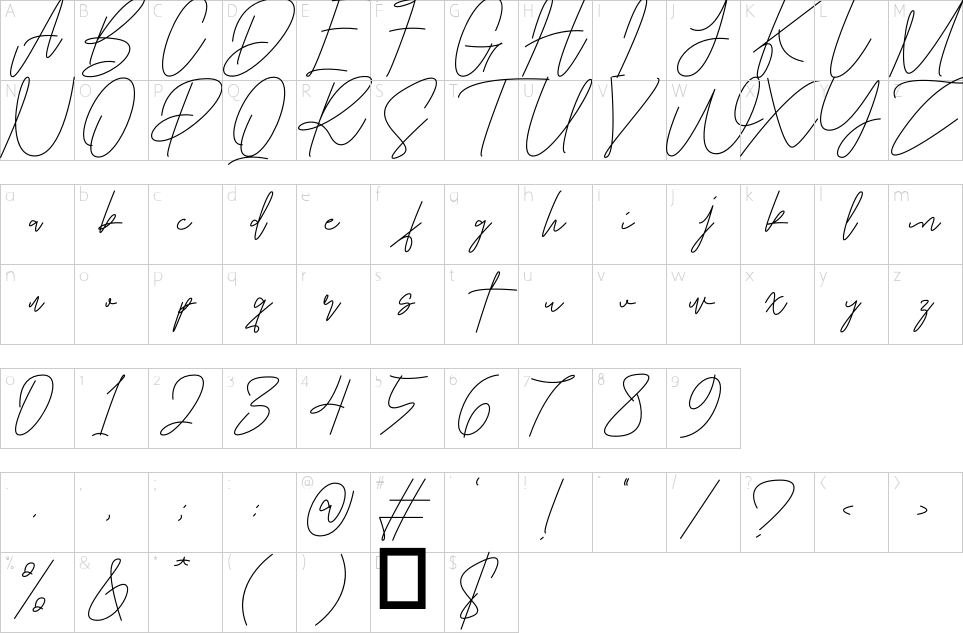
A fonte Samarotan é uma opção grata para designers, criadores de blogs e profissionais do design, oferecida gratuitamente para Windows e Mac. Criada pelo designer Jada Akbal, Samarotan foi o assunto de 1.132 baixos. Esta fonte é um belo complemento para qualquer projeto de design, proporcionando um toque único e personalizado. Composta por uma variedade de caracteres, Samarotan é perfeita para títulos chamativos ou para uso no corpo do texto, garantindo uma apresentação estética e profissional. Para quem busca estilos únicos e com versatilidade, Samarotan é uma fonte que não pode ser esquecida.